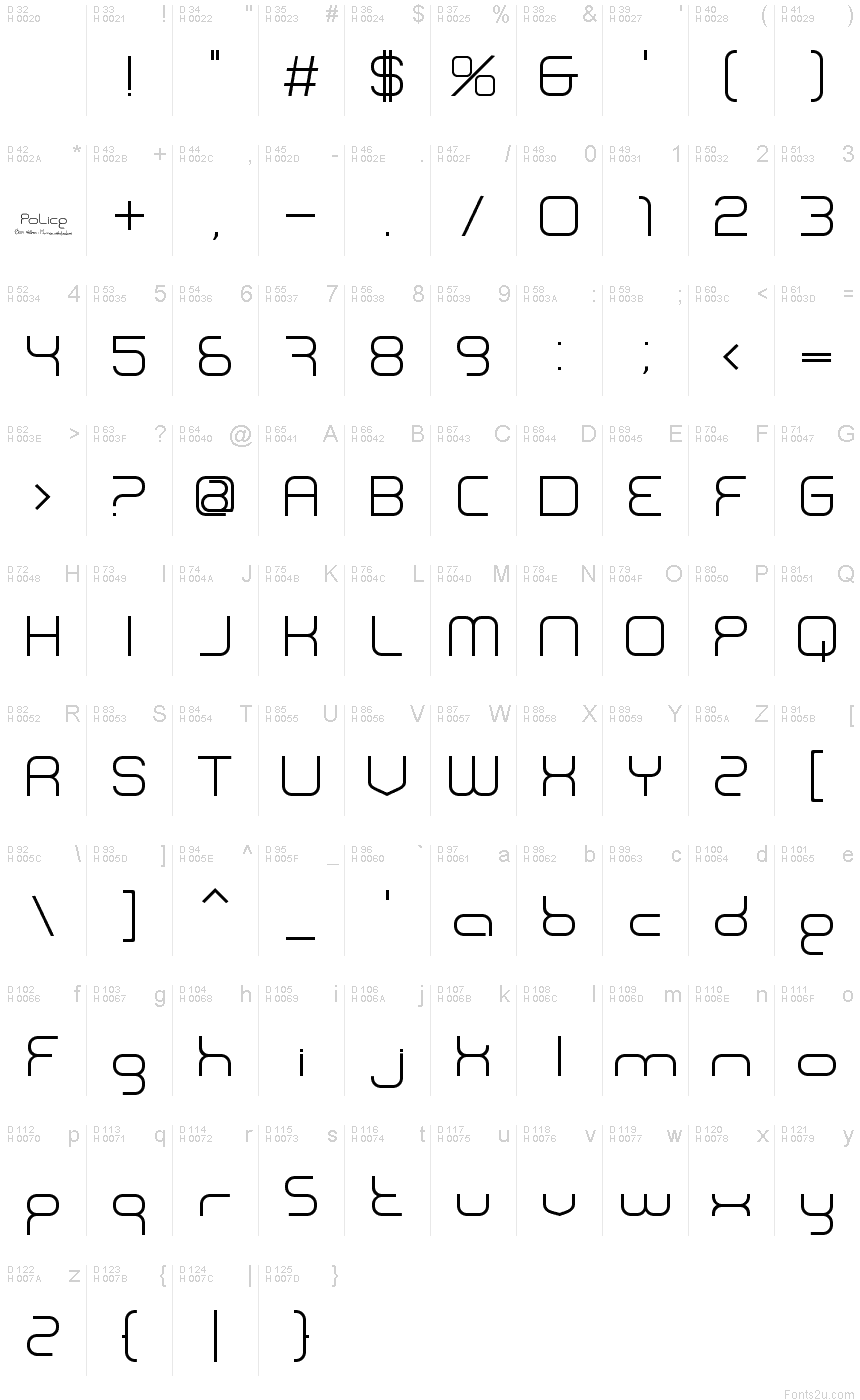
BN Police ist die kostenlose, futuristische Display-Schrift von Ben Nathan. Bestehend aus fließenden Monoline-Strichen und abgerundeten Ecken, versprüht sie den eleganten Techno-Vibe der späten 90er. Die Formen wirken modular und kontrolliert, bleiben durch die weichen Kanten jedoch nahbar statt kühl.
Sie passt perfekt zu Grafiken aus der elektronischen Musikszene, Sci-Fi-Postern, Gaming-Menüs, Tech-Branding und Magazin-Covern, bei denen ein kompaktes Wordmark einen synthetischen, aber einladenden Look braucht. Als kostenlose Schrift ist sie zudem ideal für Titelkarten und kurze Interface-Überschriften: Dank der kapselartigen Formen wirkt selbst kurzer Text wie ein durchdachtes Design-Element.